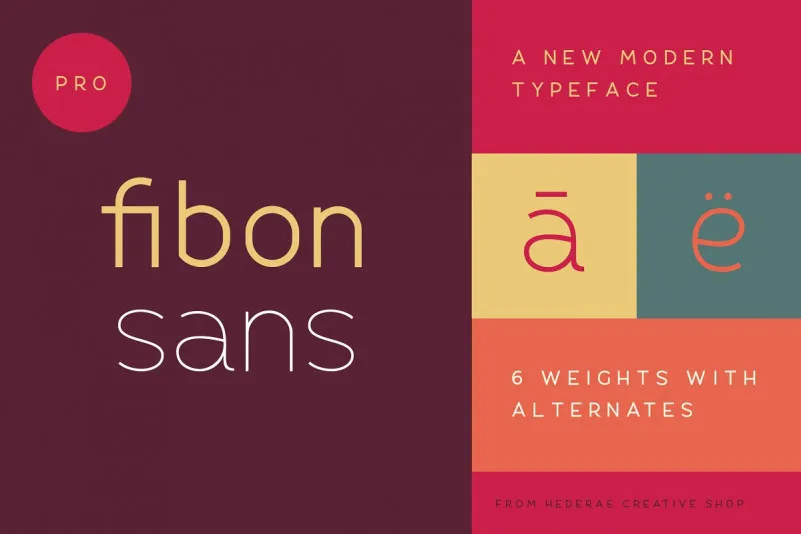
Esta é uma nova tipografia moderna, uma sans serif, que inspira-se nas antigas tipografias enquanto mantém um estilo moderno forte. A Fibon Font foi projetada e compartilhada pela Hederae Type Foundry. Ela é equilibrada, com baixo contraste, geométrica, de fácil leitura e perfeitamente adequada para uso em textos e gráficos exibidos ou impressos. Seus contornos tornam-a uma tipografia dinâmica quando se compõe um texto, ideal para quem deseja adicionar um toque moderno aos seus trabalhos. A Fibon Sans é uma escolha ótima para revistas de moda, logotipos e lojas. Suas curvas dão vida a cada página, destacando-se como uma fonte fácil de ler que traz personalidade e estilo contemporâneo sem perder sua funcionalidade essencial. Com certeza tornará seus projetos únicos e distintivos, criando um impacto visual imediato nas páginas dos seus produtos.